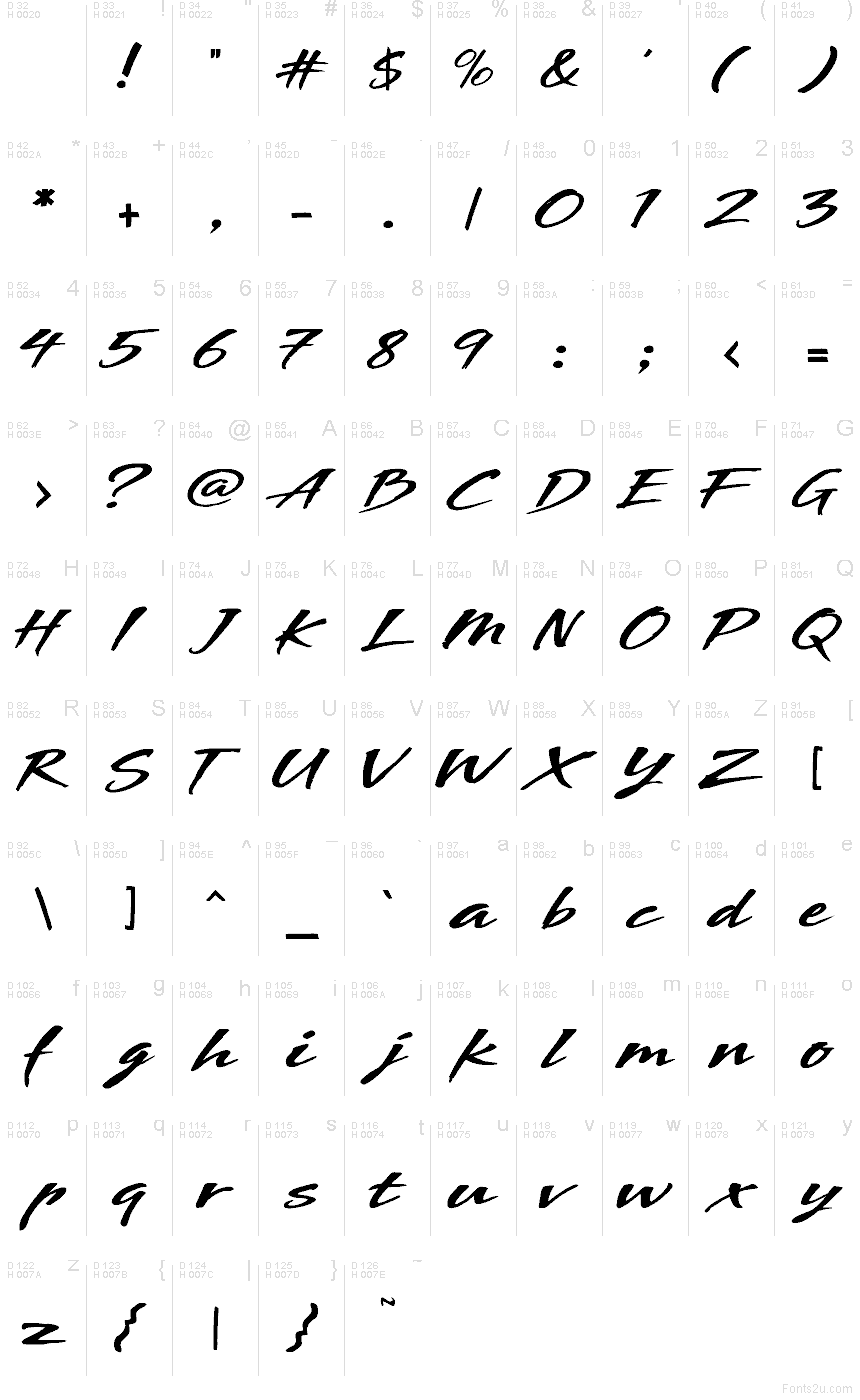
*La Cavale Solitaire* od *BlackFridayFont* je bezplatné štětcové písmo s rychlým, jistým tahem ručně psaného podpisu. Široké tahy dolů přecházejí v jemná napojení a dlouhé koncové tahy, což písmenům dodává plynulou siluetu s výrazným směřováním vpřed namísto pečlivě nakresleného, formálního vzhledu.
Módní a lifestyleové značky mohou jeho osobitý ráz využít pro loga, obaly a kampaně. Písmo působí bezprostředně a sebejistě. Jeho kombinace rychlosti a elegance se hodí také na hudební plakáty a pozvánky pro umělce, tvůrce nebo nezávislá vydavatelství s osobním příběhem.